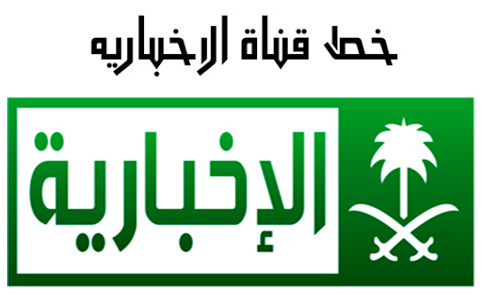
نبذه تعريفيه عن خط قناة الإخباريه
خط قناة الإخباريه هو من أكثر الخطوط تميزا وإبداعاً وهو مستنبط من الخط الكوفي
وأكثر ما يميز خط قناة الإخباريه هو أنه يجمع بين جمال وأناقة الخطوط العربيه الحديثه
وبين جمال وعراقة الخطوط العربيه القديمه التي تمثل تراث الخط العربي الأصيل
ومن مميزات خط قناة الإخباريه أن حروفه تشبه إلى حد كبيرالخط العبري.
وكذلك يشبه الخطوط الأسيويه المختلفه مثل الخط الصيني والياباني والكوري والتيلندي
ويعتبر خط الإخباريه من أجمل الخطوط التي يستخدمها مصممي الإعلانات
وهو يبرز جمال أي تصميم يتم استخدامه فيه ويعطيه لمسة عصرية حديثه ولمسه عراقه وأصاله في آن واحد .
وأكثر ما يميز خط قناة الإخباريه هو أنه يجمع بين جمال وأناقة الخطوط العربيه الحديثه
وبين جمال وعراقة الخطوط العربيه القديمه التي تمثل تراث الخط العربي الأصيل
ومن مميزات خط قناة الإخباريه أن حروفه تشبه إلى حد كبيرالخط العبري.
وكذلك يشبه الخطوط الأسيويه المختلفه مثل الخط الصيني والياباني والكوري والتيلندي
ويعتبر خط الإخباريه من أجمل الخطوط التي يستخدمها مصممي الإعلانات
وهو يبرز جمال أي تصميم يتم استخدامه فيه ويعطيه لمسة عصرية حديثه ولمسه عراقه وأصاله في آن واحد .